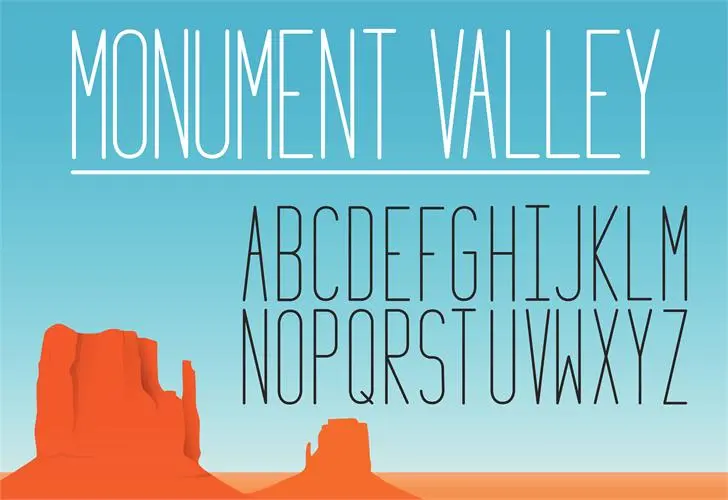
A fonte Monument Valley 1.2 é uma escolha perfeita para qualquer projeto que valoriza estilo moderno e minimalismo. Ela tem a característica marcante de ser fina, alta e futurista, tornando-a excelente para aplicações em títulos, destacando sua importância e impacto visual. Mesmo sem números ou pontuação além do uso da vírgula, ponto e aspas, ela oferece um conjunto limpo e funcional. Seja você um designer de site, uma editora digital ou mesmo um desenvolvedor web que busca elementos distintos para seus projetos, Monument Valley 1.2 não deixará você insatisfeito. Com futuras atualizações esperadas em nossa loja, há sempre espaço para evolução e inovação na sua escolha de fontes.